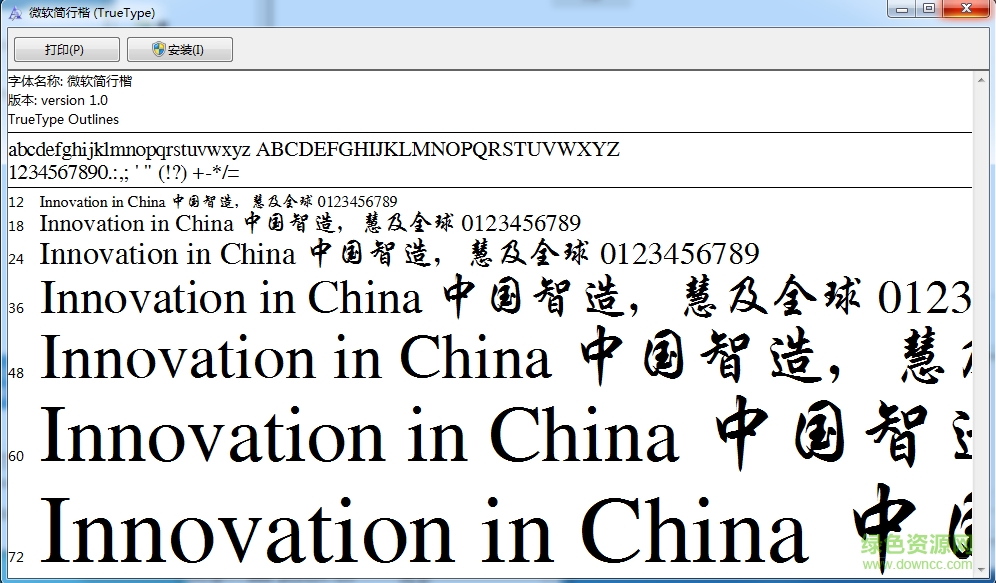
ctxingkaisj字體
ctxingkaisj在哪里下載?ctxingkaisj字體在綠色資源網(wǎng)就可下載,ctxingkaisj是一款非常端正大方的電腦字體,字體線條流暢具有美感,時刻彰顯文藝氣息。
ctxingkaisj字體介紹
字體飄逸灑脫,行筆流暢自然,剛勁舒展,書法韻味濃,適用于書籍、報刊、雜志的標題字和宣傳、裝飾用字。